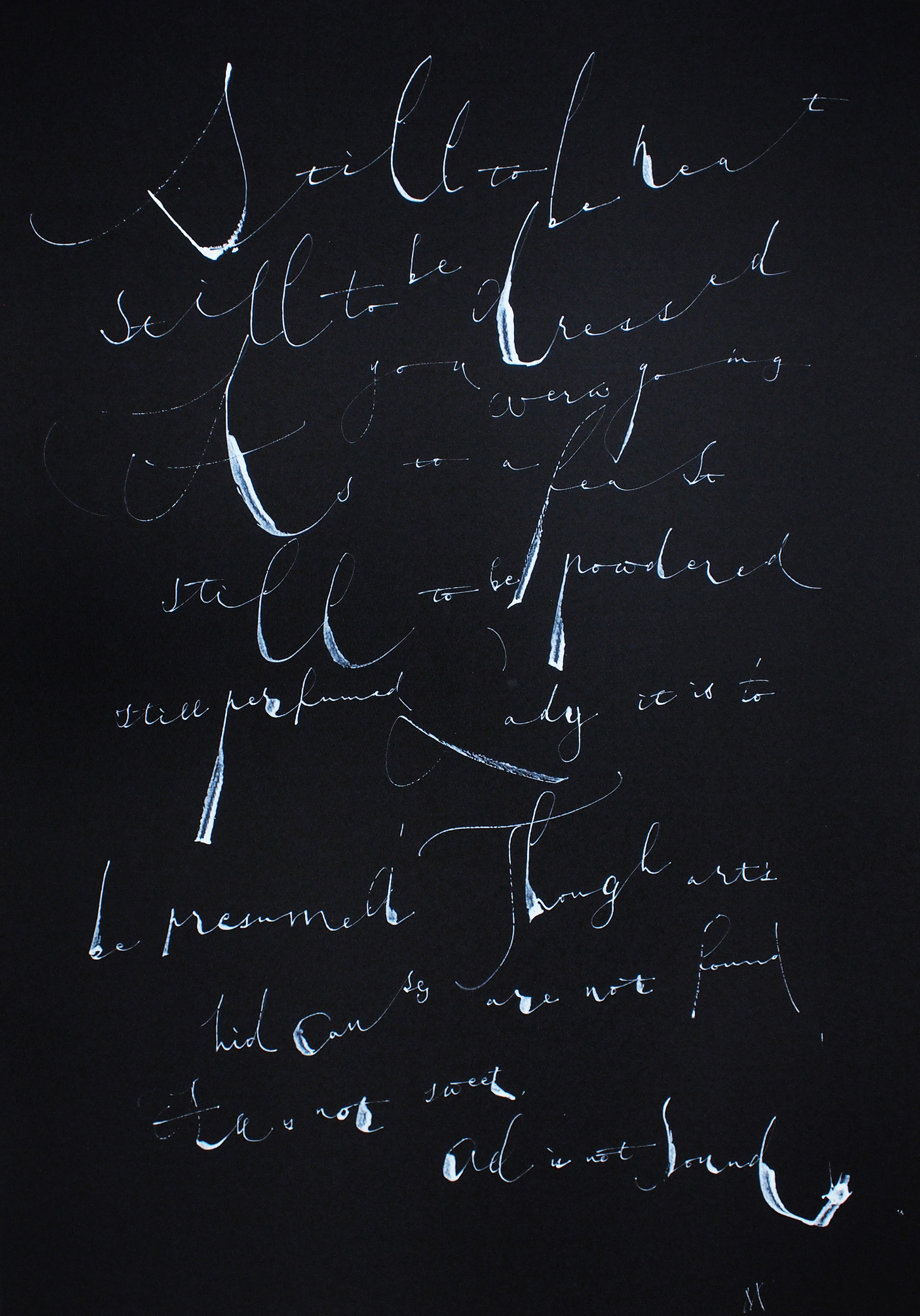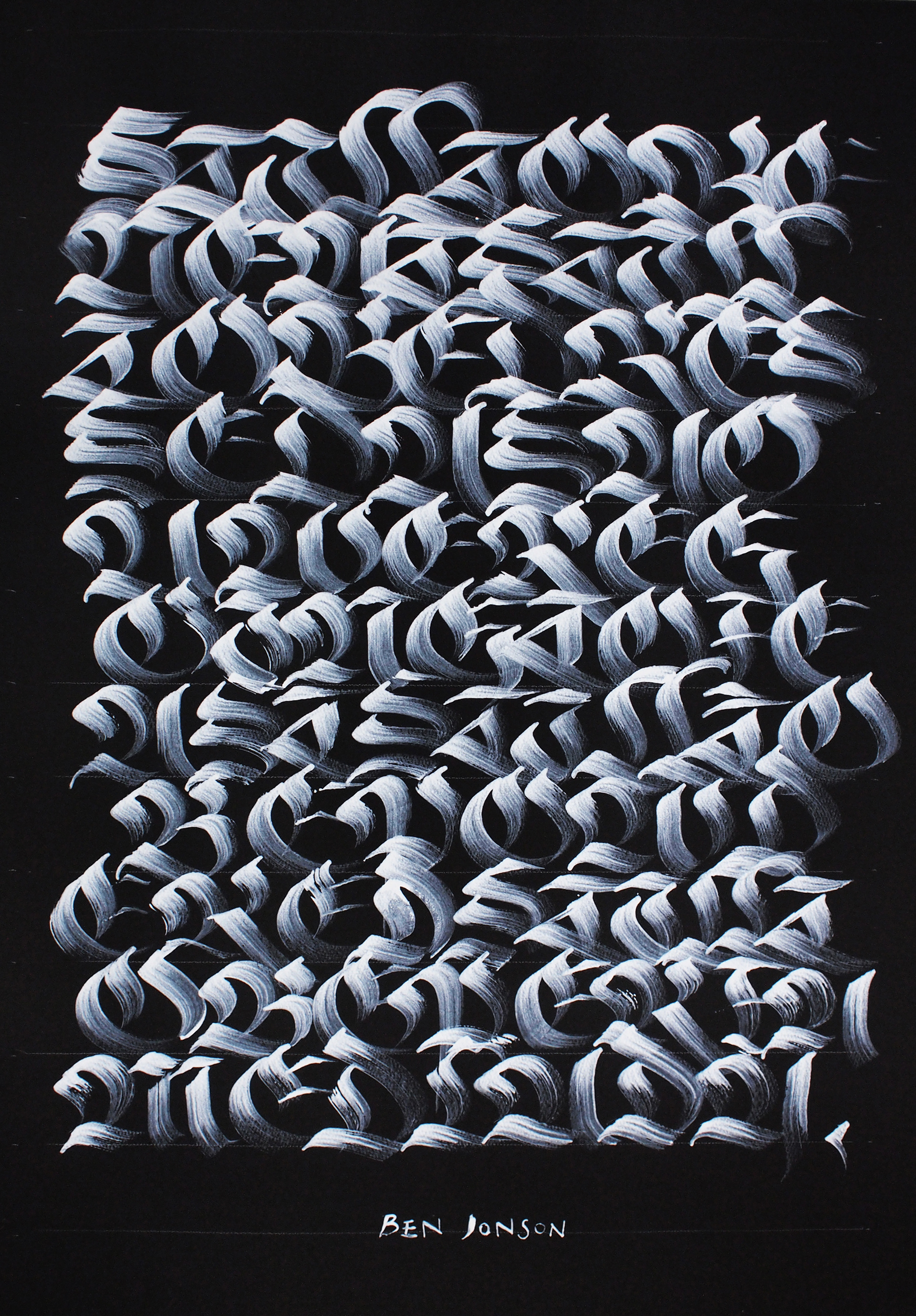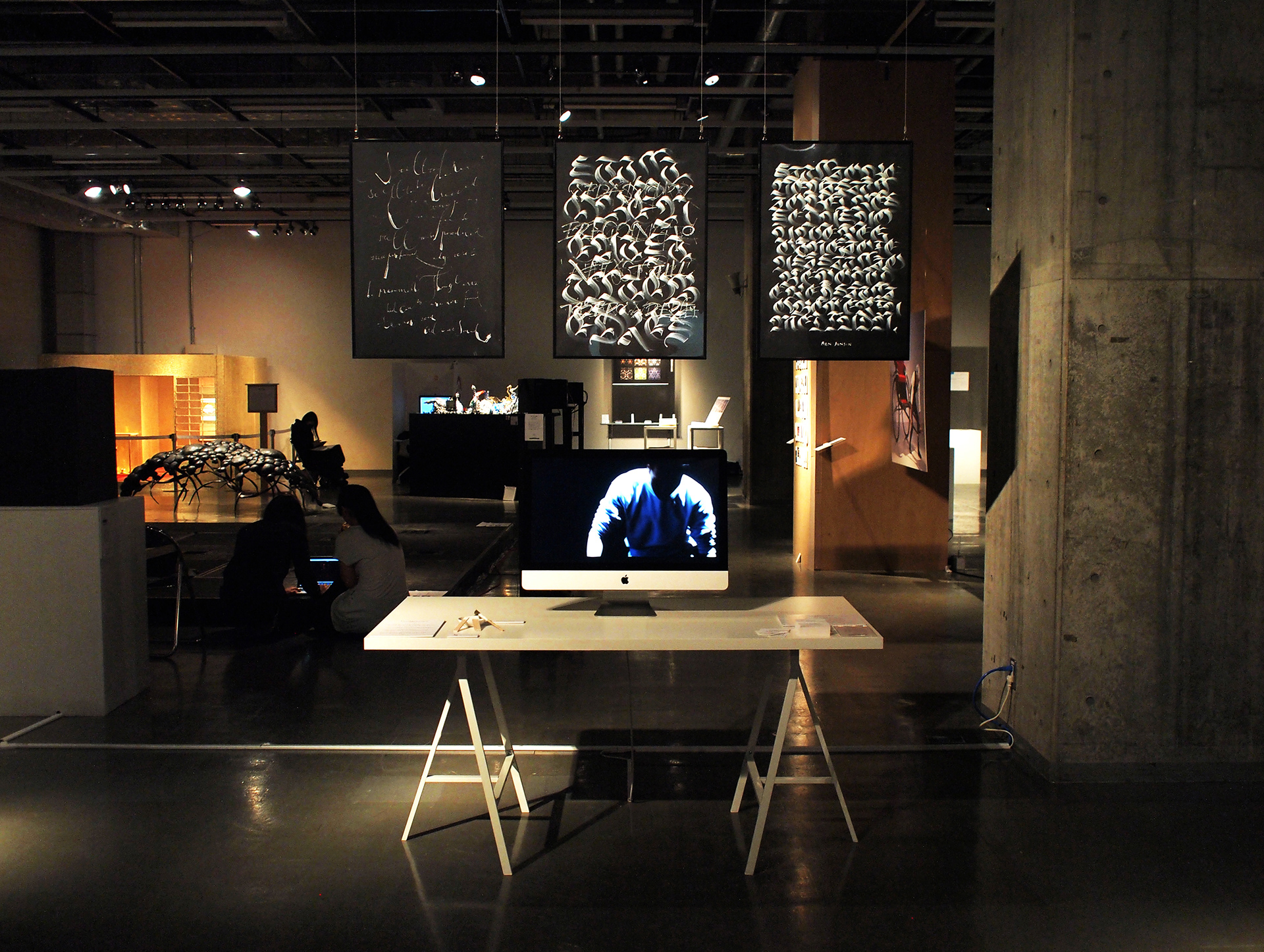
‘Lettershaping: Letters with time sequence’
Calligraphy with balsa wood and colapen.
a First Prize winner in Musashino Art University Degree Show 2014
「Lettershaping 息する時間を内包する文字」
武蔵野美術大学 卒業・修了制作展 2014
優秀賞受賞作品
デジタル環境の発展で私たちは様々な活字に囲まれているが、
欧文活字書体の背景には紀元前後から培われてきた西洋書道、
カリグラフィーの伝統がある。
システマチックに均一化されてきた現代の中で
手書き文字の芸術的価値は見直されてきている。
身体を伝わって生み出された線の集合が文字として意味をもつ、
その中であえてノイズを生み出すことは、
文字が人の手によって書かれている証明にもなる。
バルサ材やアルミ缶を用いることで、それぞれの文字に表情をあたえた。